Tổng hợp 10+ font tiếng Nhật thông dụng đẹp và hướng dẫn kích hoạt tiếng Nhật trên PC, macOS
Bạn đang gặp khó khăn trong việc lựa chọn font tiếng Nhật để làm việc hay phục vụ cho việc học? Bạn không biết nên sử dụng font chữ tiếng Nhật nào phù hợp? Hãy tham khảo ngay 10+ font tiếng Nhật đẹp và phổ biến được tổng hợp bởi FPT Shop ngay nhé!
Font tiếng Nhật là gì?
Tiếng Nhật không còn quá xa lạ trên thế giới với những chữ cái đặc trưng riêng biệt. Khác với bảng chữ cái Latinh, chữ viết tiếng Nhật gồm ba loại bảng chữ cái chính là Hiragana, Katakana và Kanji (Hán tự). Mỗi bảng chữ cái có những đặc điểm riêng, mang đậm dấu ấn của văn hóa xứ sở hoa anh đào.
Để có thể đọc và viết tiếng Nhật một cách dễ dàng, bạn cần lựa chọn những font tiếng Nhật phù hợp. Font chữ tiếng Nhật được sử dụng trong nhiều mục đích như học tập, nghiên cứu hay thiết kế sáng tạo.
Tổng hợp các font tiếng Nhật đẹp, phổ biến
1. Ms Mincho
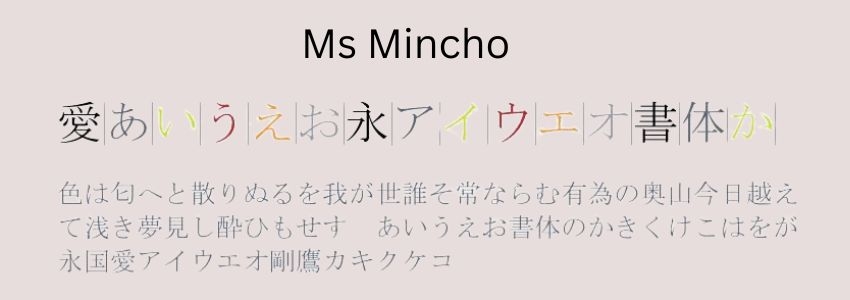
Đây là font chữ tiếng Nhật được cài đặt mặc định trên các máy tính Windows. Font chữ có thiết kế đơn giản, dễ đọc, dễ nhìn, được sử dụng nhiều trong các văn bản dài như bài luận văn, bài nghiên cứu, bài báo cáo,...
2. Epson font
Đây là bộ font chữ tiếng Nhật miễn phí được phát triển bởi công ty máy in Epson. Font chữ được sử dụng rộng rãi tại Nhật Bản phù hợp để dùng trong các loại văn bản khác nhau. Bạn có thể sử dụng trong các văn bản trang trọng hay trên các ấn phẩm mang tính thương mại, quảng cáo.
3. Hanazono
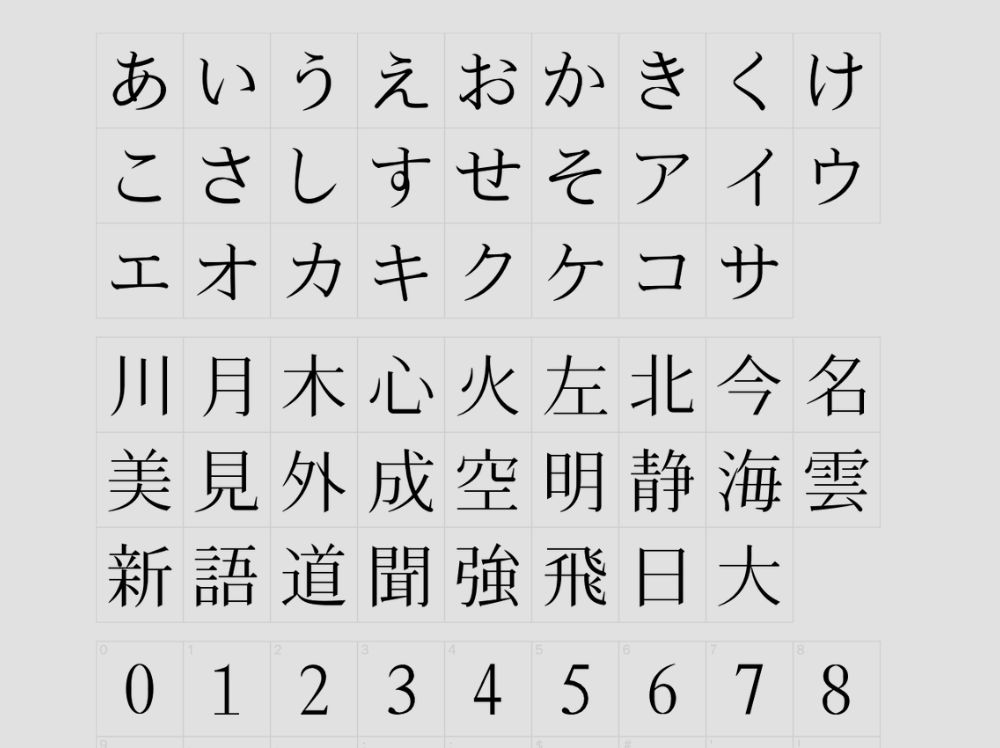
Font Hanazono được đánh giá cao bởi sự thanh thoát, nhẹ nhàng cho người nhìn. Font được sử dụng trong bộ gõ Unicode giúp tương thích với nhiều ngôn ngữ và ký tự khác nhau. Font Hanazono gồm nhiều kiểu chữ, từ các chữ cái Hiragana mềm mại, Katakana cứng cáp đến Kanji phức tạp.
4. Hkgokukaikk
Điểm nổi bật của font chữ Hkgokukaikk là nét chữ dày, đậm thể hiện được sự mạnh mẽ, khỏe khoắn giúp người nhìn dễ đọc hơn. Font được sử dụng cho chữ Furigana (gồm chữ cái Hiragana và Katakana) hỗ trợ cho việc đọc, phiên âm tiếng Kanji trong tiếng Nhật.
5. Hkgyong
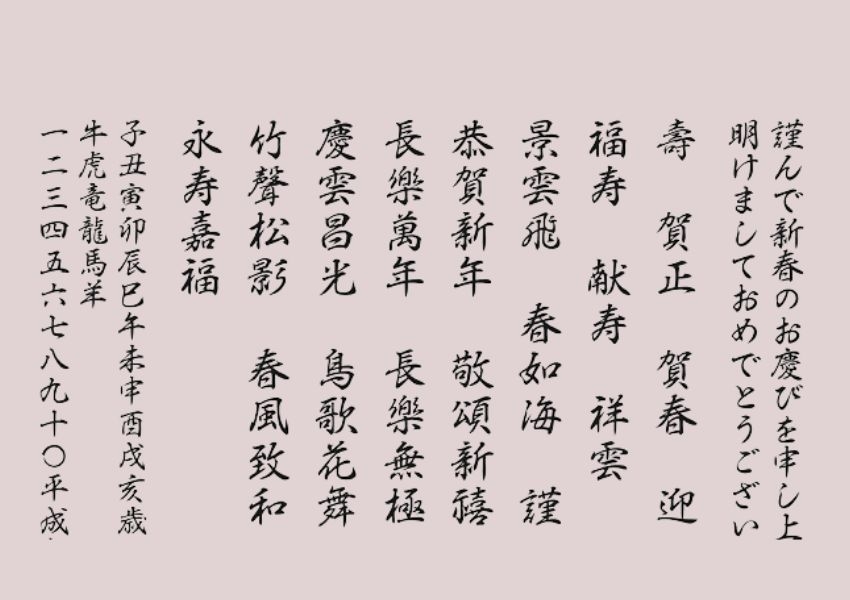
Nếu bạn là người yêu thích thư pháp thì font tiếng Nhật Hkgyong là sự lựa chọn phù hợp. Font chữ Hkgyong với đặc điểm mềm mại, đường nét uyển chuyển thể hiện sự hoài cổ, sang trọng.
6. Hkkaiiw
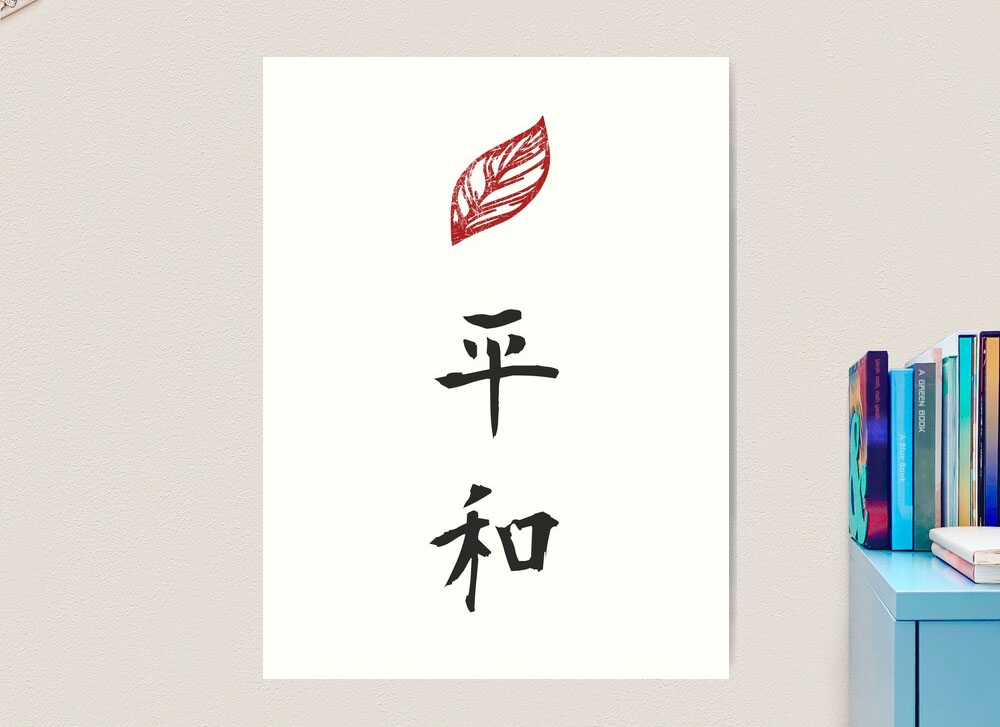
Font chữ tiếng Nhật Hkkaiiw được sử dụng nhiều trong viết thiệp hay trang trí các ấn phẩm mang đến vẻ đẹp cuốn hút người nhìn. Font thể hiện sự trang trọng nhưng vô cùng tinh tế với những đường nét rõ ràng.
7. Hksoung
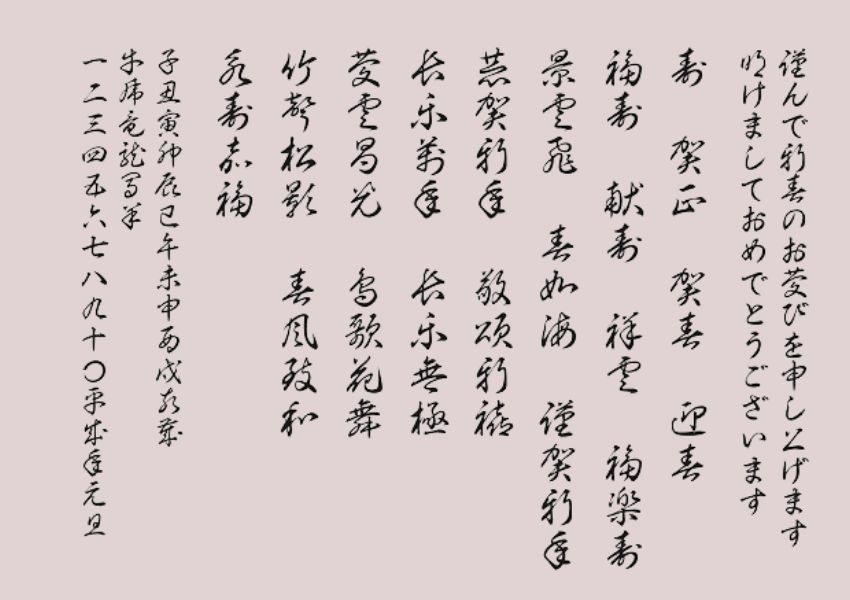
Hksoung là một trong những font chữ phổ biến được dùng trong thư pháp. Loại chữ được thiết kế theo kiểu viết láu, viết nhanh của chữ Nhật. Các nét vẽ liền mạch, hạn chế việc nhấc bút, đòi hỏi người nhìn phải am hiểu về tiếng Nhật mới có thể đọc hiểu.
8. Honoka marugo
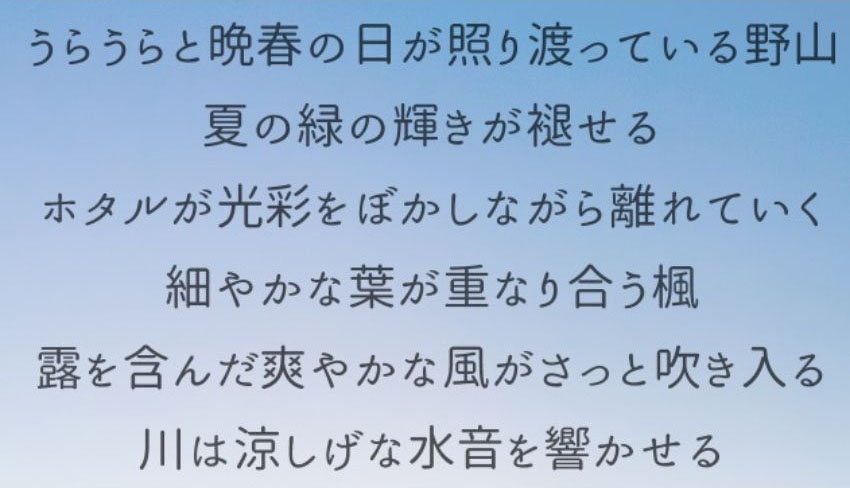
Font chữ Honoka marugo với các đường nét tròn trịa và mềm mại giúp văn bản dễ đọc hơn, ngay cả ở kích thước nhỏ. Font chữ mang đến cảm giác ấm áp, thân thiện, được sử dụng cho nhiều mục đích khác nhau.
9. Jiyuno Tsubasa
Font chữ Jiyuno Tsubasa có đặc điểm nổi bật là khá cứng cáp với các đường nét thanh mảnh, dứt khoát. Font chữ được sử dụng nhiều trong nhiều các tình huống hài hước, vui vẻ, mang đến tiếng cười cho người nhìn.
10. Kanji Stroke Order
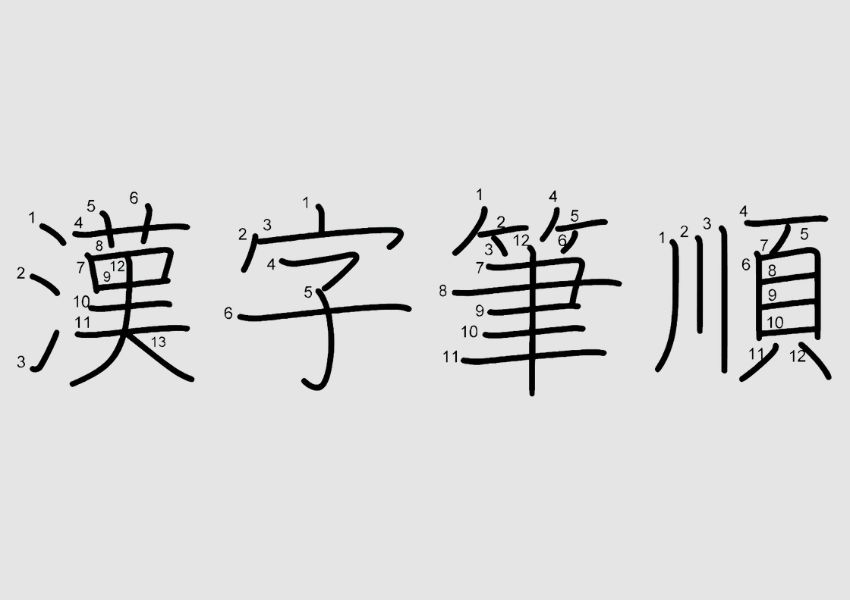
Nếu bạn là người mới học tiếng Nhật và cần luyện viết các chữ cái thì font chữ Kanji Stroke Order là lựa chọn thích hợp. Font chữ được thiết kế để hiển thị thứ tự các nét vẽ khi viết chữ cái Kanji giúp người học dễ dàng viết đúng từng nét.
11. Mini covenie
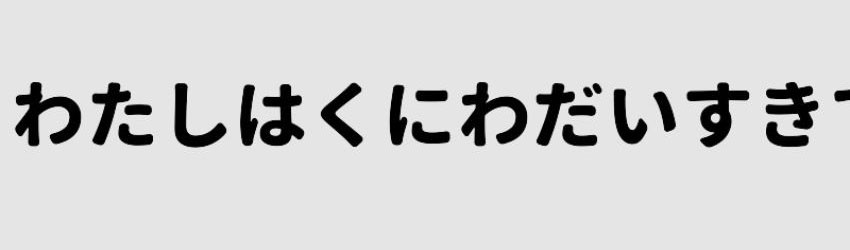
Font chữ Mini covenie nổi bật với đường nét to tròn mang lại sự dễ thương, thân thiện với người nhìn. Font chữ được sử dụng trong các bản phối banner, tiêu đề trong các bộ phim hoạt hình, sách cho trẻ nhỏ,...
12. Ms Gothic
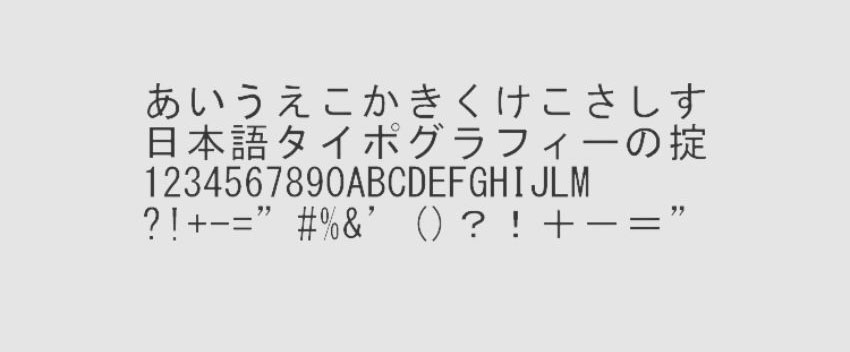
Ms Gothic được biết đến là font chữ được cài mặc định trong hệ điều hành Windows dành cho tiếng Nhật. Đây là font chữ Sans Serif với các đường nét đậm giúp người nhìn dễ đọc hơn. Font gồm nhiều biến thể với các kiểu dáng đa dạng từ Regular, Bold đến Italic, Bold Italic nhằm đáp ứng mọi nhu cầu của người dùng.